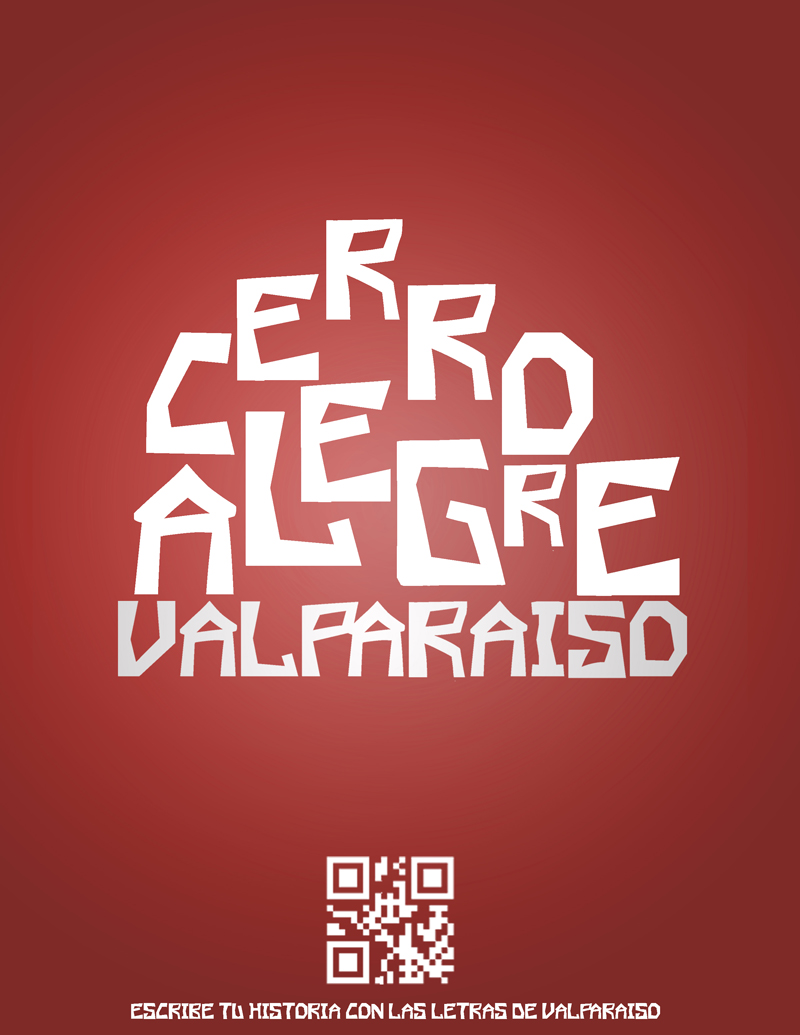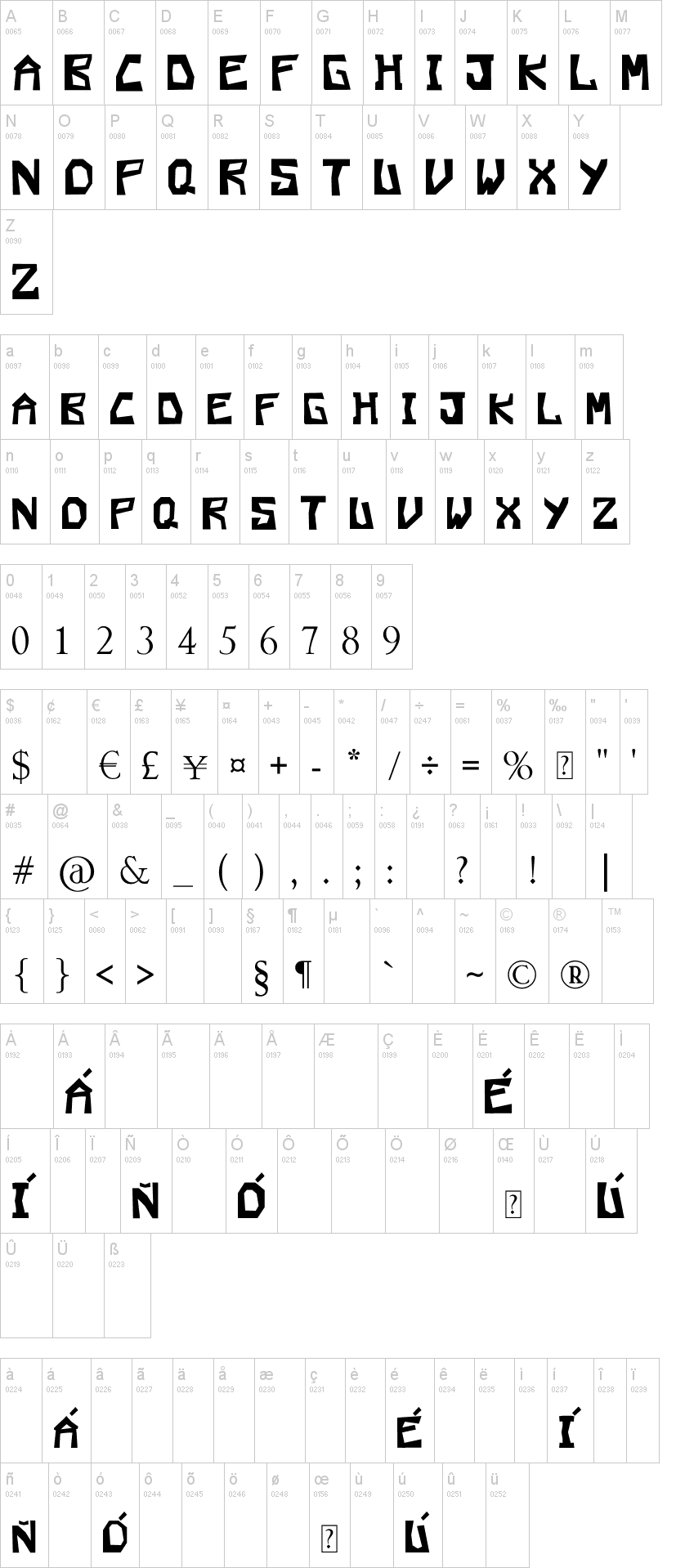
Note of the authorEsta letra tiene una significancia especial, fue creada bajo un trabajo fotográfico, en el cual se realizo una escurcion en la ciudad de valparaiso, en donde se tomo un registro fotográfico y en base a este registro se genero VALPARALETRA.